れいに始まり、和で終わろう。2019年今年の漢字®「令」の年に
京都に本部を置く日本漢字能力検定協会がその年の世相を表す漢字ひと文字を一般から募集し、最も多かった字が選ばれる「今年の漢字®」の2019年では、12月12日に「今年の漢字R」が発表され、およそ21万6,000の応募数の中から令和の「令」の文字が選ばれた。
京都市東山区の清水寺で森清範貫主により大きな和紙に筆で「令」の文字が書き上げられた。
日本漢字能力検定協会は「令」が選ばれた理由として新しい元号の「令」和に明るい時代を願う国民の思いが集約されたとしている。さらに法「令」改正による消費増税や芸能界で起きた闇営業、薬物使用などの問題で法「令」順守が重視されたこと、自然災害で警報や避難勧告の発「令」が相次いだことも挙げている。
清水寺の森清範貫主は、「元号がかわり、皆さんの気持ちが新しくなったのではないかと思う。これからの時代も皆で仲よく、力を合わせて生きていかなければいけないと改めて感じた」と話した。
2番目に多かった文字は、新しいという「新」、3番目はクロちゃんのギャグ「クロちゃんです!ワワワワー」でお馴染み令和の「和」となっている。
▼草書の「令」ほか
▼楷書の「令」ほか
地震・台風・豪雨…、2018年今年の漢字®「令」の年に
2018年12月12日に今年1年の世相を漢字1文字で表す「今年の漢字®」が京都の清水寺で「災」と発表された。
「災」が選ばれた理由として、地震・豪雨・台風など、災害の経験から全国的に防災意識が高まり、多くの人が自助、共助の大切さを再認識した年であること。また、仮想通貨の流出やスポーツ界のパワハラ問題、財務省決裁文書改ざんなどが発覚し、多くの人がこれらの出来事を人災や災いと捉えた事によるとのこと。
キタ━━━━(゚∀゚)━━━━!!今年の漢字®2017年
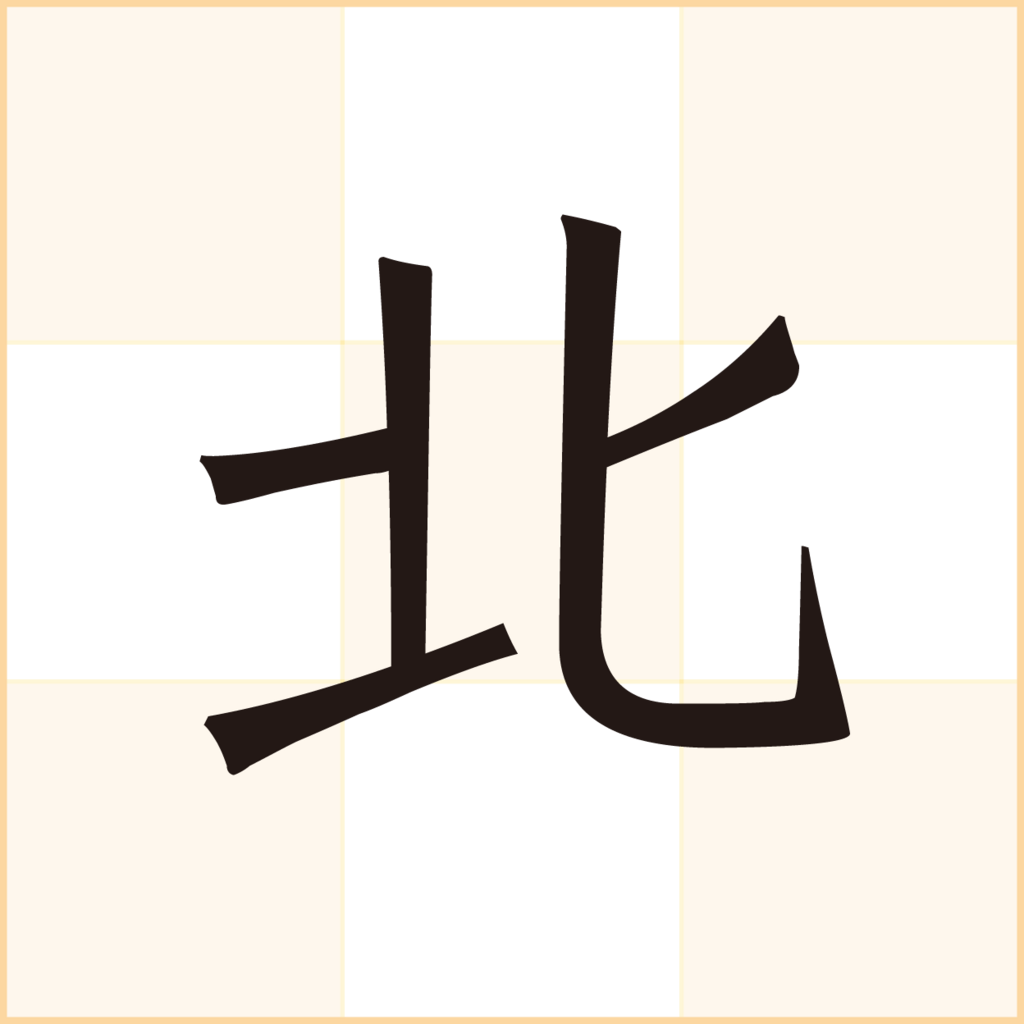
日本漢字能力検定協会は12月12日全国から募集した「今年の漢字®」を京都・清水寺で発表した。応募総数は15万3594票に及び、最多得票は「北」は7,104票となり、2017年の漢字は「北」に決定した。
同協会は「北」が選ばれた選考理由として、弾道ミサイル発射や核実験強行など「北」朝鮮による脅威や九州「北」部豪雨による被害、天候不順で「北」海道産ジャガイモが不足し、ポテトチップスの一部が販売中止になったこと、プロ野球・北海道日本ハムの大谷翔平選手が米大リーグに移籍し、早稲田実業高から清宮幸太郎選手が入団、競馬で「キタ」サンブラックが活躍したことなどによるものだとしている。
応募の2位は「政」(3,571票)、3位は「不」(3,323票)、4位は「核」(3,138票)、5位は「新」(2,958票)と続いた。
京都・清水寺で和紙に「北」を書き上げた森清範貫主は、「『北』という漢字は2人が背を向けている姿を表している。同じ2人でも『仁』はお互い話をし、平和な世の中を築こうという仁愛に通じる。話し合いをしなければ思いは通じない。平和に向かって努力することが大事だ」と感想を述べた。
北朝鮮以外にじゃがいもや大谷君を理由に北海道、キタサンブラックなど挙げられているが、ほぼほぼ北朝鮮が理由で間違いない気がしたが、メルカリが2017年の「トレンドワード」を発表し、前年と比較して検索数が急上昇したワードのランキングで1位となったのが「ピザポテト」だった。トレンドワード1位となった理由に4月に起きた「北」海道産ジャガイモの収穫量減少の影響から販売休止が発表されて直後、メルカリでの検索が増加したことが理由として挙げられているので、少なからず「北」海道 票も入っての見解は間違いではないのかもしれない。
ダイナフォントの「北」魏楷書
上記で掲載した「北」の文字は、ダイナフォントの北魏楷書を使用した。北魏楷書はダイナフォント「龍門石碑体」をベースに、ウェイトを細く修正した書体。龍門石碑体の特徴を踏襲した北魏楷書は、ストローク元来の凛とした勢いを持ちながら、独特な気品を醸し出し、古風な感覚を喚起させた伝統製品、或は冠婚葬祭などの場合に最適な書体になっている。
今年の漢字®:2016年「金」の文字が読めないと話題に!
今年の漢字®の2016年「金」だったが、発表式にて清水寺の住職・森清範貫主により書かれた文字がこの文字が読めないと話題になった。
そこで読めない文字として定評のある草書フォントで入力してみた。
使用した草書フォントはダイナフォント草書霜月。
楷書にすると下記のようになる。